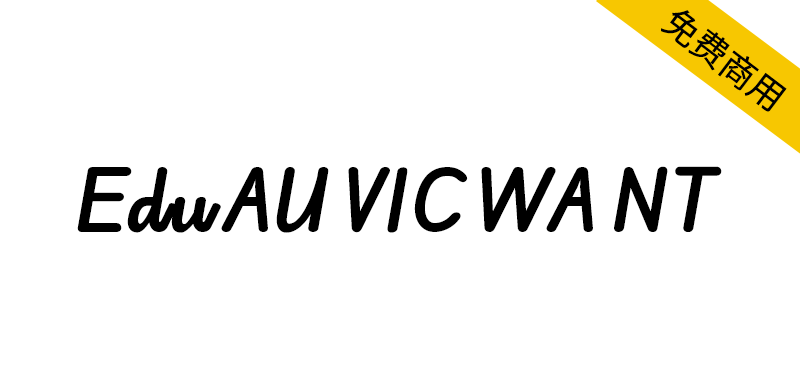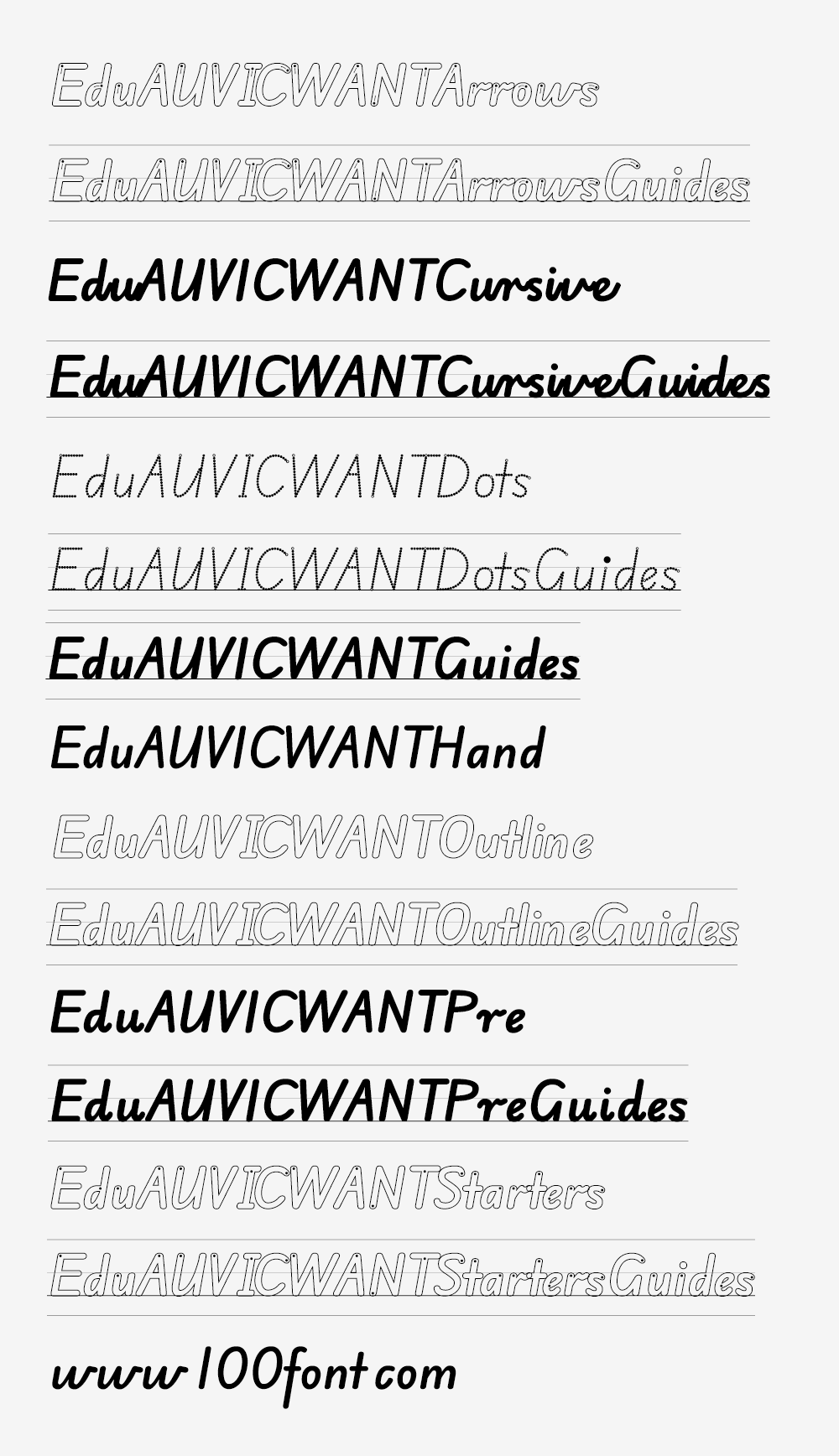
Edu AU VIC WA NT(VICWANTSchoolhandAustralia)旨在支持西澳大利亚州、西北地区和澳大利亚维多利亚州提供的教学手写字体。
This font family is made to support handwriting instruction as offered in Western Australia, Northwest Territory, and Victoria, Australia.